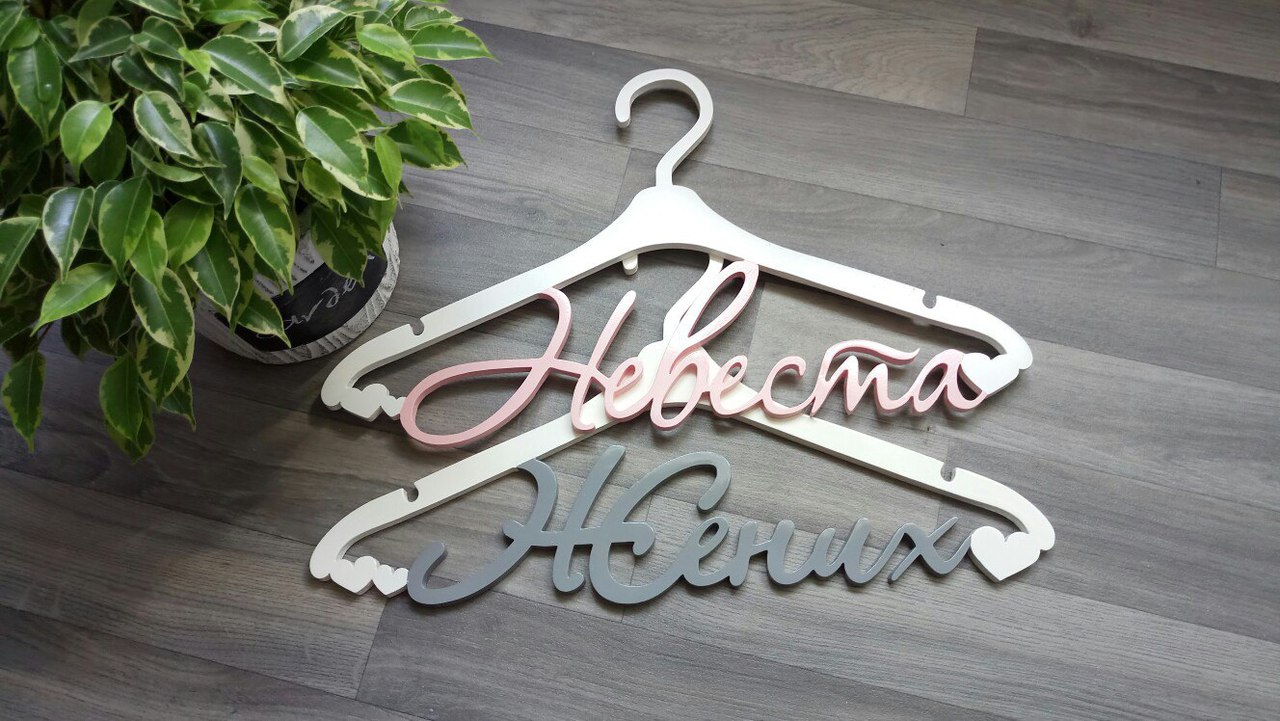
Gelin ve damat askıları için özel olarak tasarlanmış, akıcı ve zarif el yazısı fontu. Lazer kesim projelerinizde, düğün dekorasyonlarında ve ahşap isimlik tasarımlarında mükemmel sonuçlar verir.
Lazer Kesim Düğün Askısı Script Font Tasarımı